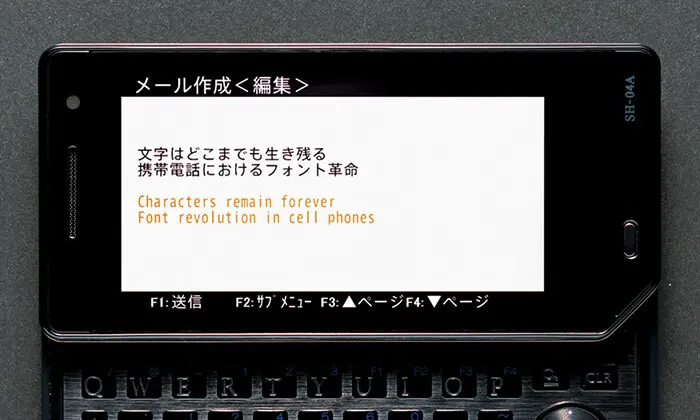
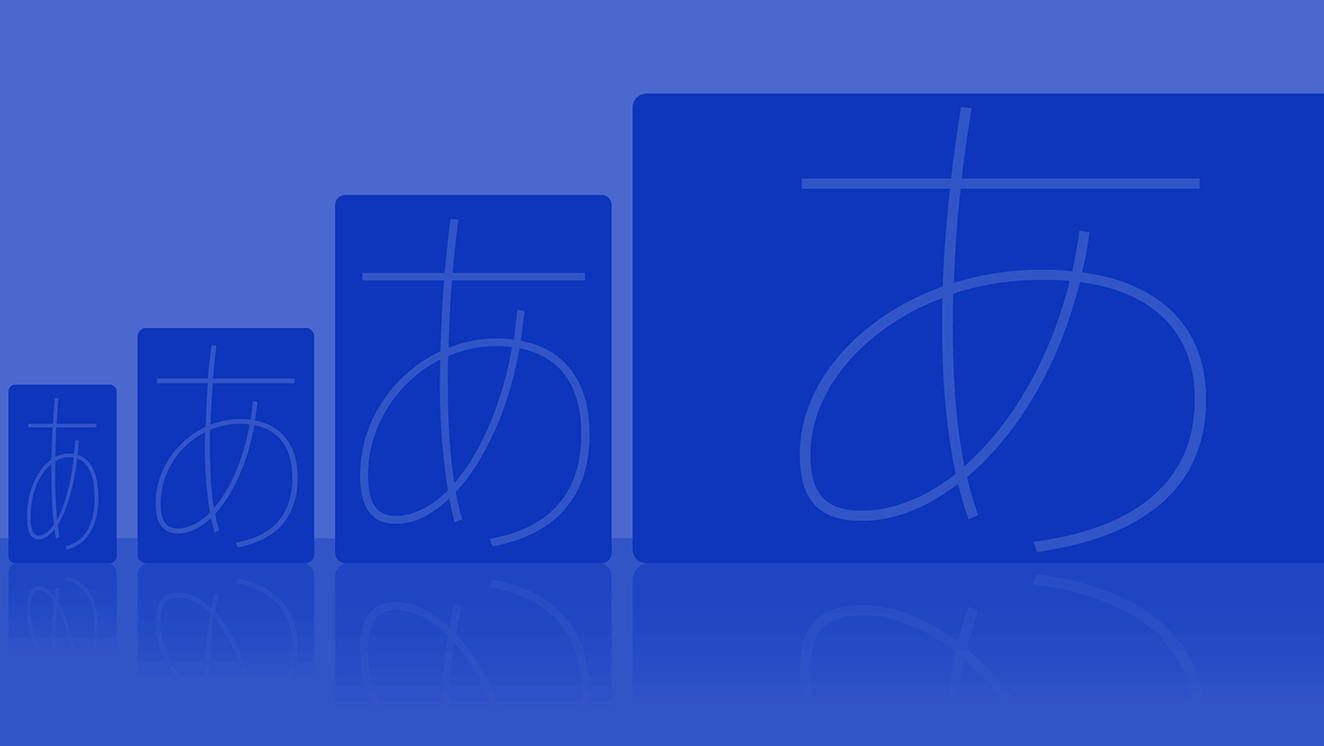
組込みフォント
技術の進展に則したアプローチにより、
デジタル製品の価値を高めるフォントを提供します
ウエアラブル端末やゲームなど
さまざまな製品でタイププロジェクトのフォントを
スマートフォンやタブレット、自動車のインストルメントパネルやデジタルサイネージなど、さまざまなディスプレイ装置でフォントを目にする機会が増えています。モニタの高解像度化とデバイスの小型化など、表示環境のデジタル化にともなってフォントに求められる機能も高度化してきました。タイププロジェクトでは、UIやウエアラブル端末などの機器、アプリケーションやゲーム、サーバーへの搭載などの用途で、さまざまな搭載ライセンスを提供しています。
ユーザーインタフェースに
知的で明快な表情を
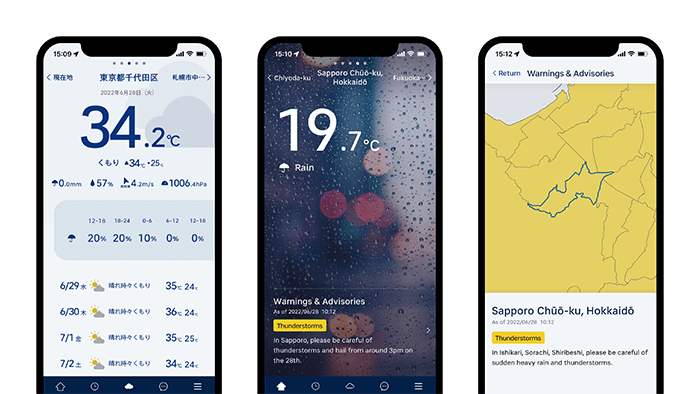
シンプルで読みやすいサンセリフ書体であるAXIS Fontは、ユーザーインタフェースに知的で明快な表情をもたらします。7ウエイトが揃っているため、スマートフォンやタブレットなどで、デザインの一貫性を保ちながら幅広い表現に対応できます。また、ゴシック体に近い表情を持つTP明朝ローコントラストは、情報機器のディスプレイなど、これまで主にゴシック体が使われてきた領域に明朝体という選択肢を広げます。
コンデンスとコンプレスで
情報空間の経済効率を
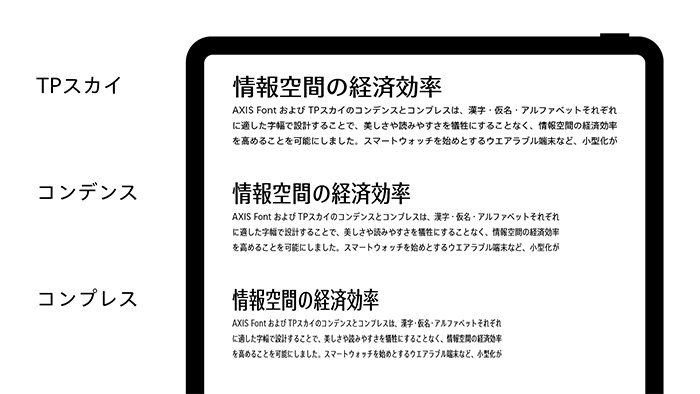
AXIS FontおよびTPスカイのコンデンスとコンプレスは、漢字・仮名・アルファベットそれぞれに適した字幅で設計することで、美しさや読みやすさを犠牲にすることなく、情報空間の経済効率を高めることを可能にしました。スマートウォッチを始めとするウエアラブル端末など、小型化が進む情報機器で、大きな効果を発揮します。TP明朝は、ディスプレイのサイズや解像度などに応じて可読性をコントロールすることができ、電子書籍リーダーなどの横組み用書体に最適です。
ビットマップフォントと
TrueType
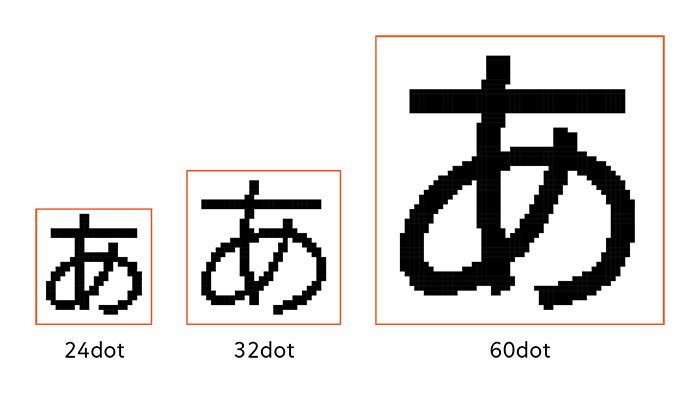
モニタの高解像度化とデバイスの小型化などにより、フォントに求められる機能も高度化しています。タイププロジェクトの提供する組込みフォントのフォーマットはOpenTypeが基本ですが、レンダリングエンジンへの対応によりビットマップフォントやTrueTypeでの提供や、特殊な文字や記号を追加するなどさまざまなご要望に対応しています。